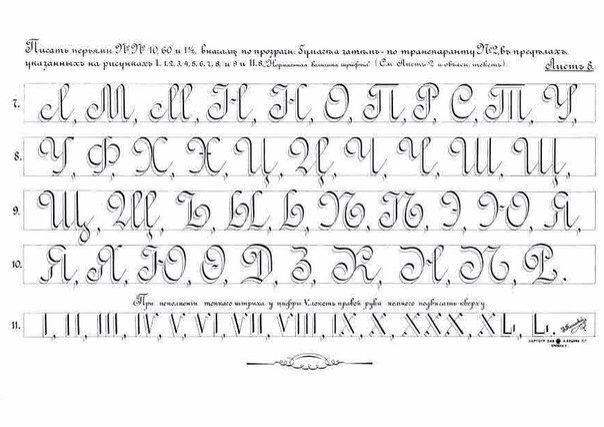
Рукописный шрифт — шрифт, литеры которого выглядят как буквы написанные от руки.
С помощью рукописных шрифтов имитируют надписи выполненные от руки различными пишущими инструментами — карандашом, ручкой, пером, кистью. Рукописные шрифты получили большое распространение в различных поздравлениях, приглашениях и оформлении надписей праздничных мероприятий.
Рукописные шрифты имеют и один недостаток, их труднее воспринимать визуально, а следовательно, читать большие тексты сложнее. Это следует учитывать при выборе начертания шрифта для оформления текста, поэтому рукописные шрифты следует использовать в заголовках, отдельных фразах и в небольших текстах, для придания строкам отдельного внимания и значимости. Для средних и больших текстов лучше использовать стандартные, легко читаемые шрифты, чтобы не утомлять читателя.
Проверка имени, характерного для PostScript
В Acrobat Distiller выполняется поиск шрифта PostScript по имени, после чего он добавляется в документ PDF. Имена шрифтов PostScript чаще всего перечислены в таблице имен шрифтов. (В таблице имен хранится такая информация о шрифтах, как имя, стиль и авторские права.) Если имя PostScript недоступно, в Acrobat Distiller используется системное имя для шрифта. Например, если исходный документ содержит шрифт, установленный на компьютере, Acrobat Distiller выводит параметры BaseFont и FontName из таблицы имен шрифтов.